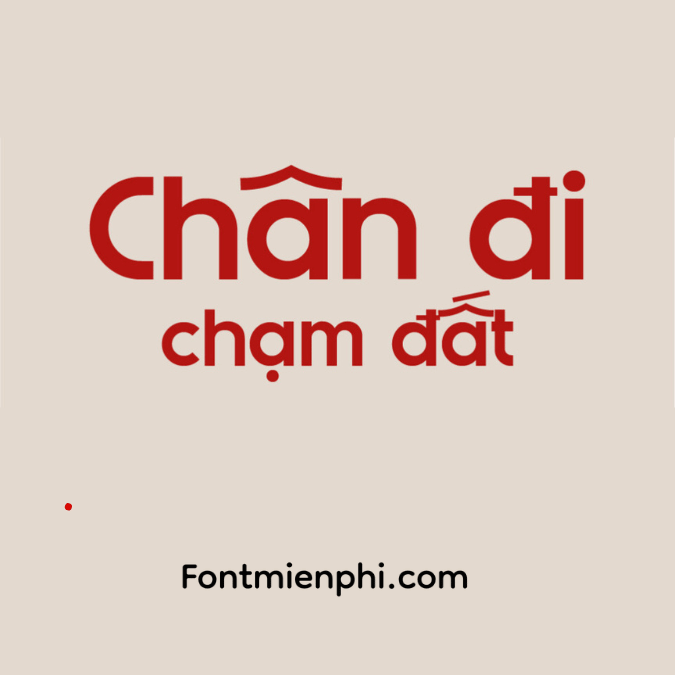
Font Việt hóa 1FTV HF Gesco
Mô tả Font Việt hóa 1FTV HF Gesco – Tết
Font 1FTV HF Gesco là một kiểu chữ được thiết kế đặc biệt để phục vụ cho việc sử dụng trong các dịp lễ Tết. Với phong cách hiện đại và dễ đọc, font này mang đến cảm giác ấm áp, thân thiện, rất phù hợp cho những lời chúc Tết, thiệp mời hay các sản phẩm quảng cáo trong dịp lễ hội.
Font 1FTV HF Gesco là một trong những font chữ Việt hóa đẹp, thuộc dòng Gesco, được thiết kế với nét chữ thanh thoát, phù hợp cho nhiều mục đích sử dụng như thiết kế đồ họa, in ấn, quảng cáo, và trình bày văn bản tiếng Việt.
2. Đặc điểm nổi bật Font Việt hóa 1FTV HF Gesco ,font tết:
- Đảm bảo hiển thị chính xác dấu tiếng Việt (ă, â, đ, ê, ô, ơ, ư…).
✅ Kiểu chữ sắc nét, dễ đọc:
- Nét thanh đậm cân đối, phù hợp cho cả tiêu đề và văn bản dài.
- Thiết kế tinh tế, mang phong cách hiện đại nhưng vẫn giữ nét truyền thống.
✅ Đa dạng ứng dụng:
- Thiết kế logo, banner, poster.
- Trình bày tài liệu, báo cáo, CV.
- Làm font chữ nghệ thuật trong in ấn, quảng cáo.
4. So sánh với các font Việt hóa khác:
| Đặc điểm | 1FTV HF Gesco | UVF (Arial/Times VN) | VNI (VNI-Times) |
| Độ sắc nét | ⭐⭐⭐⭐⭐ | ⭐⭐⭐⭐ | ⭐⭐⭐ |
| Phong cách | Hiện đại, thanh lịch | Cơ bản, phổ thông | Cổ điển |
Ứng dụng thực tế:
- Thiết kế menu nhà hàng, bảng hiệu.
- Làm CV, profile công ty.
- Dùng trong các dự án in ấn, sách báo.
Nhận xét chung: 1FTV HF Gesco là font chữ Việt hóa chất lượng cao, phù hợp cho cả dân thiết kế và người dùng phổ thông.